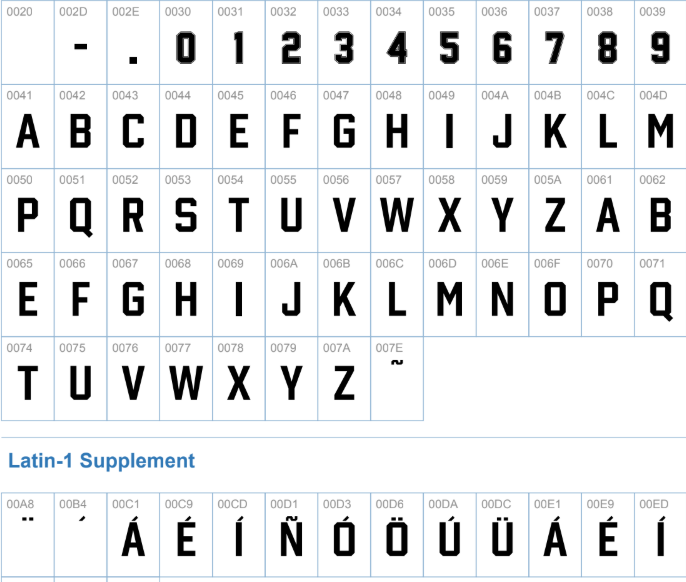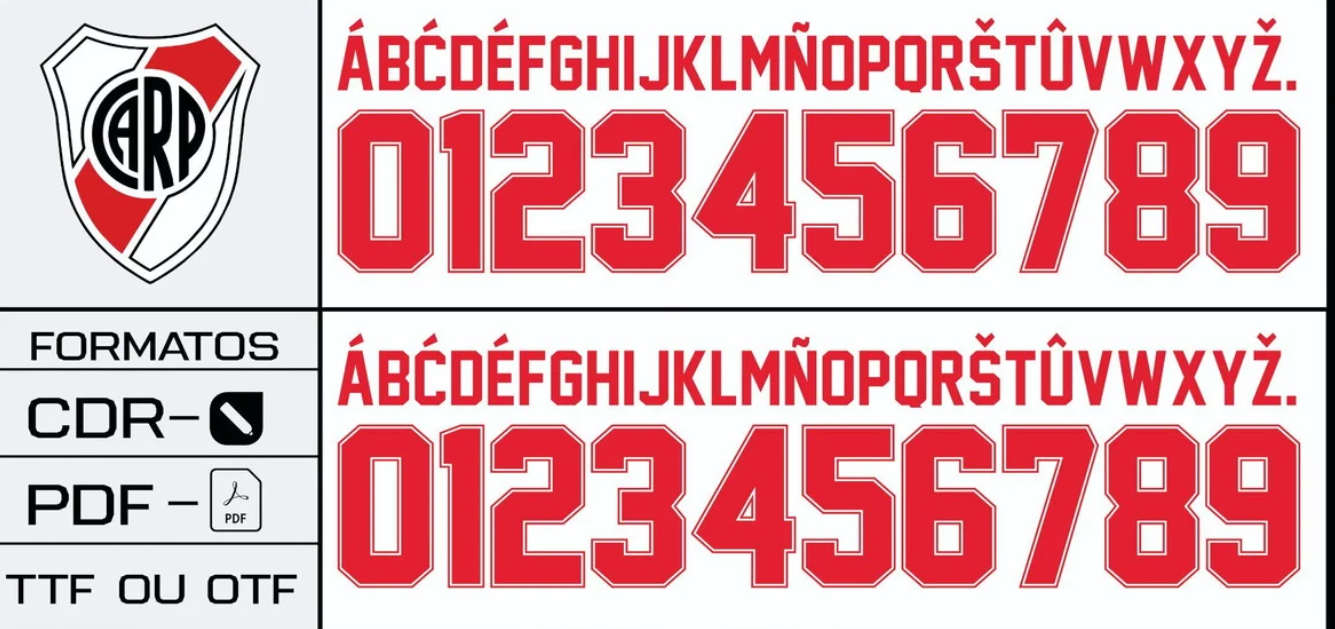
Quando se fala em peso e tradição na América do Sul, a camisa do River Plate é uma das primeiras que vêm à mente. Para a temporada 2024/2025, a Adidas renovou o manto do Millonario, trazendo uma estética que respeita a histórica “Banda Roja” (faixa vermelha) mas atualiza a tipografia para os padrões globais da marca.
Neste post, você encontra o arquivo completo da fonte utilizada na Primera División e na Libertadores, essencial para quem trabalha com personalização de camisas e busca o detalhe exato dos uniformes usados no Monumental de Núñez.
Estilo Visual e Aplicação
A tipografia escolhida pela Adidas para o River Plate nesta temporada segue um design moderno e industrial, alinhado com o template global da marca alemã para seus principais clubes de elite (Elite Teams).
A fonte apresenta traços sólidos e levemente condensados, garantindo excelente legibilidade à distância. O grande diferencial visual está nos cortes angulares internos dos números e na espessura robusta, que cria um contraste perfeito tanto na camisa titular (branca com faixa vermelha) quanto no uniforme alternativo. É a fonte ideal para criar mockups realistas ou estampar nomes de ídolos como Borja ou Mastantuono.
Dica de Design: Para um acabamento 100% fiel ao original, utilize o contorno (stroke) na mesma cor da fonte ou em contraste, dependendo se a aplicação for na camisa Home ou Away.